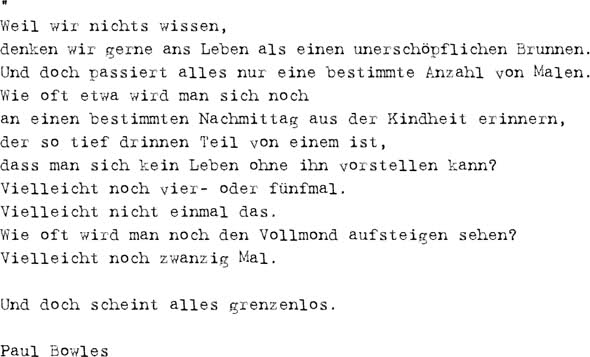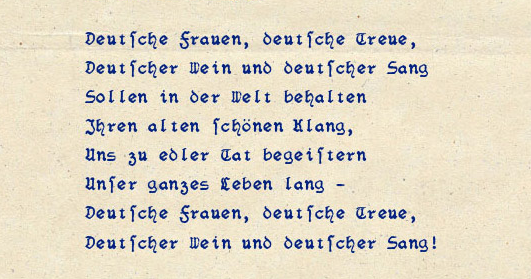
Schreibmaschinen-Schriften (sauber und dreckig)?
ich bin auf der Suche nach Schriften, die Schreibmaschinen "simulieren" (also nicht einfach nur serifenbetonte, sondern wirklich mit Quetschrand etc).
Kennt jemand ein paar Alternativen zur Auswahl? Es wären sowohl saubere Formen als auch "zerstörte" (zugeschmierte Punzen, abgebrochene Buchstabenteile, etc.) gesucht.
also ich weiß nicht, dan.
ist es nur, weil du dort arbeitest, oder findest du diesen komischen univers monospace schnitt wirklich geil?!
ich find ihn einfach nur daneben ...
Ach, komm schon. Die Univers Typewriter ist richtig geil! Vor allem wiel diese komische Schnitte echt zu die heilige Universfamilie gehören!
Alle Schreibmaschinenfonts sind ein bißchen verwirrend und außer Kontrolle.Ich finde, dass die Univers Typewriter echt cool mit Massentext aussieht.
leider kann ich nicht beurteilen, wie sie im mengentext aussieht;
die pdf samples von linotype sind da nicht besonders hilfreich.
aber monospaced fonts im mengentext sind ja sowieso nicht gerade optimal lesbar.
meiner meinung nach ist der schnitt einfach unnötig. nur weil er monospaced ist,
sieht er noch lange nicht nach schreibmaschine aus. für mich sieht es eher nach
einer kranken univers aus. und gerade die wunderbare nüchternheit der univers
kommt in den ungewöhnlichen formen des i und des l völlig abhanden.
außerdem fällt das r um.
und wenn ich mir m zu n anschaue, finde ich es in diesem fall besonders gequetscht.
die thesis und die fago, die noch am ehesten nach schreibmaschine aussieht,
finde ich auf jeden fall homogener.
wahrscheinlich ist die univers tatsächlich zu heilig.
aber im thread wurde ja sowieso nach etwas anderem gesucht, denke ich.
Die Vorschläge sind sehr brauchbar, damit ist mir eigentlich geholfen.
Ich hatte die Magda vor ein paar Jahren schon mal "in Bearbeitung", sie ist aber wieder in Vergessenheit geraten...
zur Univers-Mono-Geschichte: ich denke sowas ist nett, wenn ein Unternehmen die Univers als Hausschrift besitzt, und z.B. ein code-listing in einer Dokumentation setzen sollte. Das sieht dann zum einen übersichtlich aus, weil eben monospaced, zum anderen CD-konform, weil eben Univers.
Sprich: für besondere Anwendungszwecke ist diese Variante durchaus legitim.
Das selbe gilt natürlich auch für andere Schriften, sei es die Thesis mit ihrer mono-Variante, oder was sich sonst noch so an gut ausgebauten Schriftfamilien tummelt.
Ich denke wenn man als Schriftgestalter schon den ganzheitlichen Ansatz einer Schriftfamilie als Ziel hat, gehört auch eine Mono-Variante mit dazu. Schriftfamilien haben ja den Zweck, in möglichst allen möglichen Anwendungsgebieten einen einheitlichen Eindruck zu erzeugen, sei es Info-Text, Lesetext, Hervorhebungen oder eben Spezialfälle wie Code-Listings.
Außerdem sidn Monospaceschriften gerade bei Rechnungen oder ähnlichem sinnvoll wenn Ziffern untereinanderstehen müssen.
das ist zwar ein Faden aus der Gruft, aber vielleicht ist das ja für den Einen oder Anderen wieder aktuell?
Volker Busse hat einige nette Fixweiteschriften (manche Namen fangen mit F25 an) und man findet diese Schriften bei den üblichen Verdächtigen. Tipp: Daisy-Wheel. Eine leicht angematschte Letter Gothic Billich-Version.
(und weise darauf hin, dass der Faden von 2005 stammt und wieder ausgegraben wurde).
Versalziffern sind grundsätzlich (also von Ausnahmen abgesehen) »auf gleiche Kegelbreite gegossen«, da braucht es keine Monospace-Schriften. Eigentlich sind Versalziffern ja Tabellenziffern, und es ist eine traurige typographische Verirrung, daß sie sich auch außerhalb des Tabellensatzes derartig gegen Mediävalziffern durchgesetzt haben, daß sie heute als die »normalen« Ziffern wahrgenommen werden. Dazu haben natürlich auch die Schriftgießer / -gestalter beigetragen, die jahrzehntelang hauptsächlich Versalziffern geschnitzt und geliefert haben.
Fraktur-Schreibmaschinen waren aber schon eine Nazi-Marotte (eben vor 1941) — oder wie jetzt? Vor 1933 hergestellte Maschinen waren anscheinend ein ziemliches Nieschenprodukt. In den Unterlagen meiner Vorfahren befinden sich jedenfalls hunderte schreibmaschinengeschriebener Dokumente sowohl geschäftlicher als auch privater Natur aus unterschiedlichsten deutschen Quellen — aber kein einziges ist in Fraktur.